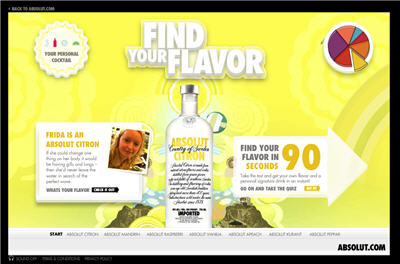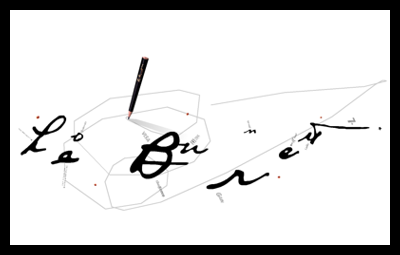
web FLASH ที่พลิกตำนานโลก
5. Rookienet ( http://www.rookienet.com )
ไม่ใช่ Flash แต่เป็น เวปศูนย์รวมเว็บ Flash ทั้งไทย และ เทศ  Layout html ชั้นพระครู พลิกโฉมวงการ webdesign เมืองไทยจากหน้ามือเป็นหลังหู  อู้ว คน copy Layout ของ Rookienet เยอะมาก ๆ ด้วย Design ไม่เกรงใจคนเฒ่าคนแก่ ปุ่มเล็กปิ๊ด อักษรเล็กจนอาจต้องใช้แว่นขยายอ่านได้
เป็นแรงบันดาลใจของใครหลายคนเหมือนกัน กับ
Rookienet โอ้ไม่ได้เข้าไปดูนานแล้วเหมือนกัน
Newwebpick นิตยสารออนไลน์ ของแท้ ( www.newwebpick.com)
เนี่ยล่ะ ๆ ๆ ๆ นิตยสารออนไลน์ของจริง ต้องออกมารูปแบบนี้
Newwebpick ออนไลน์แม็กกาซีน รวมงานกราฟฟิกระดับเทพจากทั่วมุมโลก ถ้าเป็นนิตยสารจริง ๆ (กระดาษ) ผมว่าราคาไม่ต่ำกว่าเล่มละ 2000 บาทแน่นอน แต่นี่โหลดกัน ฟรี ออกมาได้ 3 เล่มเท่านั้น
ดูงานกราฟฟิกก็คุ้มแล้วครับ รูปล้วน ๆ ไม่ค่อยมี text ให้อ่าน ซึ่งดีมากๆ สำหรับ อังกฤษกระเหรี่ยงดอย อย่างผม
เว็บนี่ครับ  เข้าไปดูแล้วปลง :05:  เมื่อไหร่ตูจะทำได้อย่างไอ้พวกนั้นบ้างวะ   :16:
เริ่มทำเว็บตอน ป.5 อ่ะ
คือ ป.4 แม่กลับจากเมืองนอก ซื้อคอมมาตัวนึง แล้วก็ได้เริ่มเล่นเนท พอ เล่นๆไป เว็บไทยก็น้อย ที่มีๆก็พิมพ์ภาษาไทยวิบัติ ผิดเยอะ เลยอยากแก้มันให้ถูก   :08: (บ้ามั้ย)
ป. 5 เมื่อไปอบรมทำเว็บ ก็ได้ front page 98 มา ซื้อหนังสือเล่มปึ๊กๆ มา 2 เล่ม นั่งอ่านๆ ทำๆ ตามไป
ใน thai.net ใช้นู่นนี่เยอะไปหมด สุดท้ายก็ เฮ่อออ  :05:
ปล. เว็บฟ๐นต์ล่มไปหลายวัน ต้องออกแบบเสื้อยืดโปรโมทเว็บเปิดใหม่ช่วงที่ผ่านมาพอดี  :08: ใช้ tx_jello ที่มีอยู่ตัวเดียว ไม่เจ๋งเลย  :23:
เหล้าเจ้านี้ ทุ่มงบทำเว็บและทุ่มงบจ้างนักออกแบบมาสนุกกันมากที่สุดของโลกเลยละมั้ง
นานๆ จะเข้ามาดูที แต่ดูทีก็ไม่ต้องไปไหนละ ขี้แตกคาเก้าอี้อยู่นั่นเอง
เว็บ absolut หน้าแรกตรง term&condition ใช้ฟอนต์อะไรหว่า
ใช่เลยๆๆ +1
พอดีมันเป็น font โปรดตระกูลนึงครับ รองจาก helvetica  :22:
เว็บเกี่ยวกับการเก็บ ข้อมูลของอุปนิสัยอย่างหนึ่ง ของผู้ใช้คอม
ชอบไอเดีย มั่กๆ  :12:
:05: ตูไม่ได้กดอะไรเลยนะ